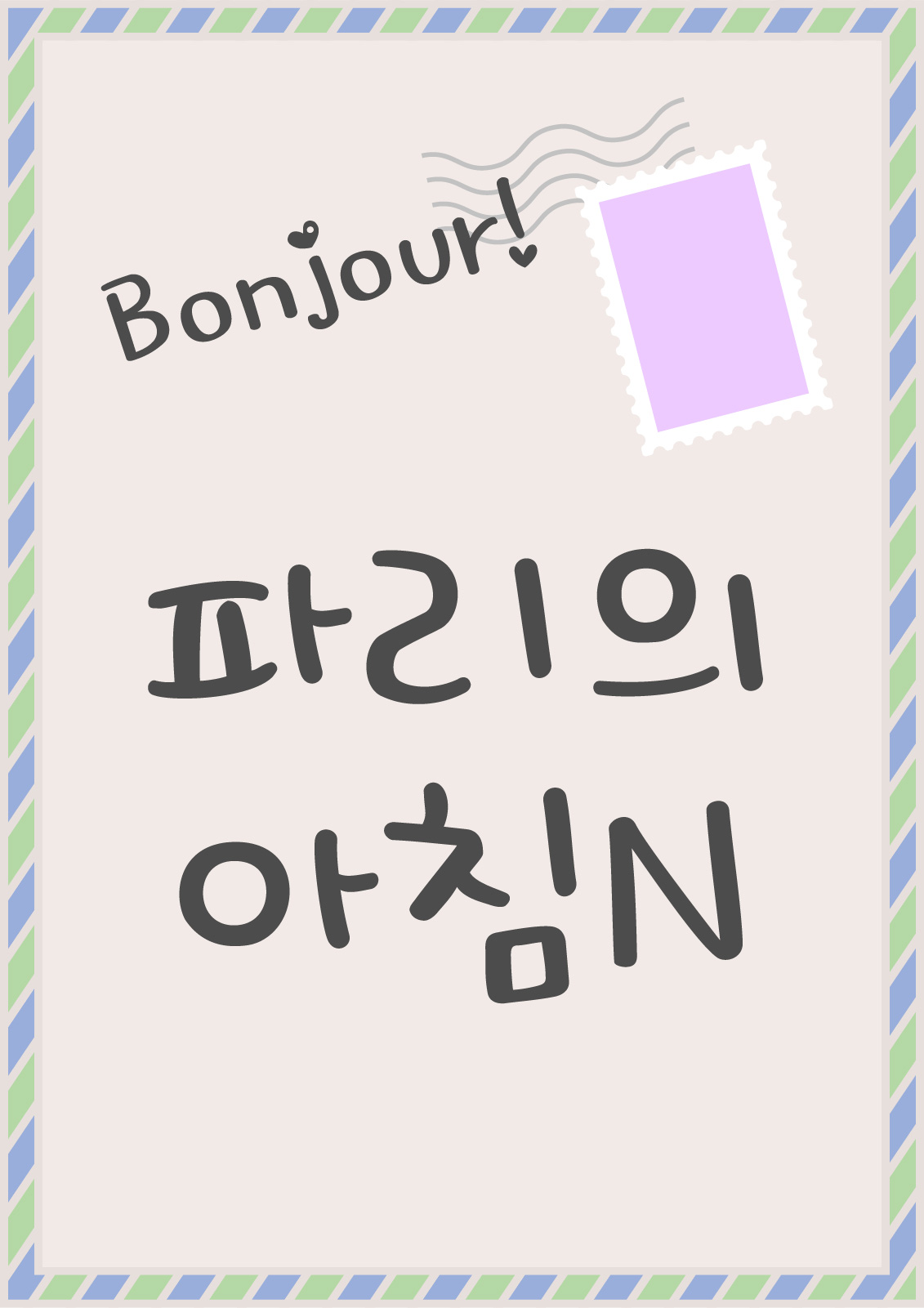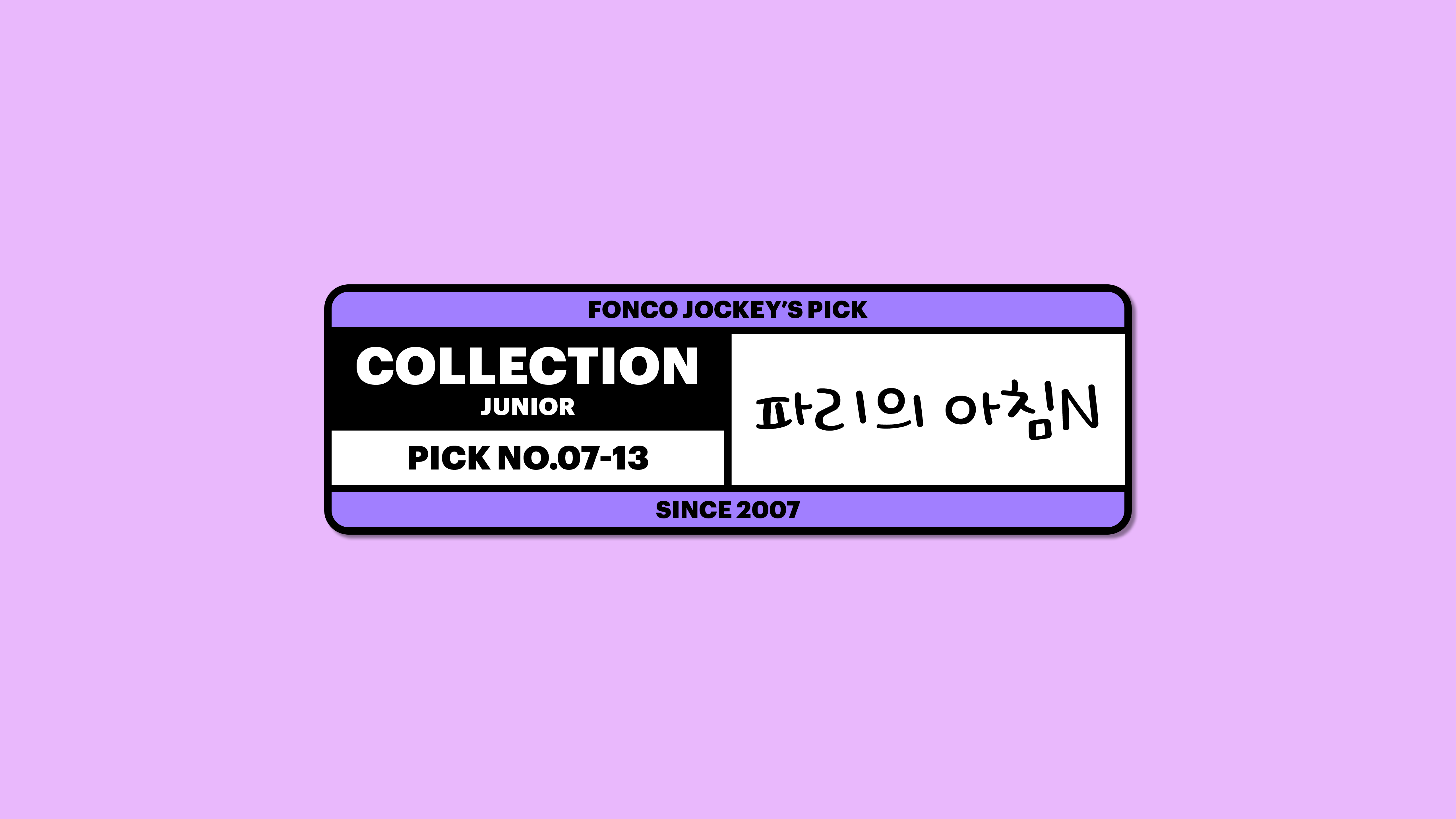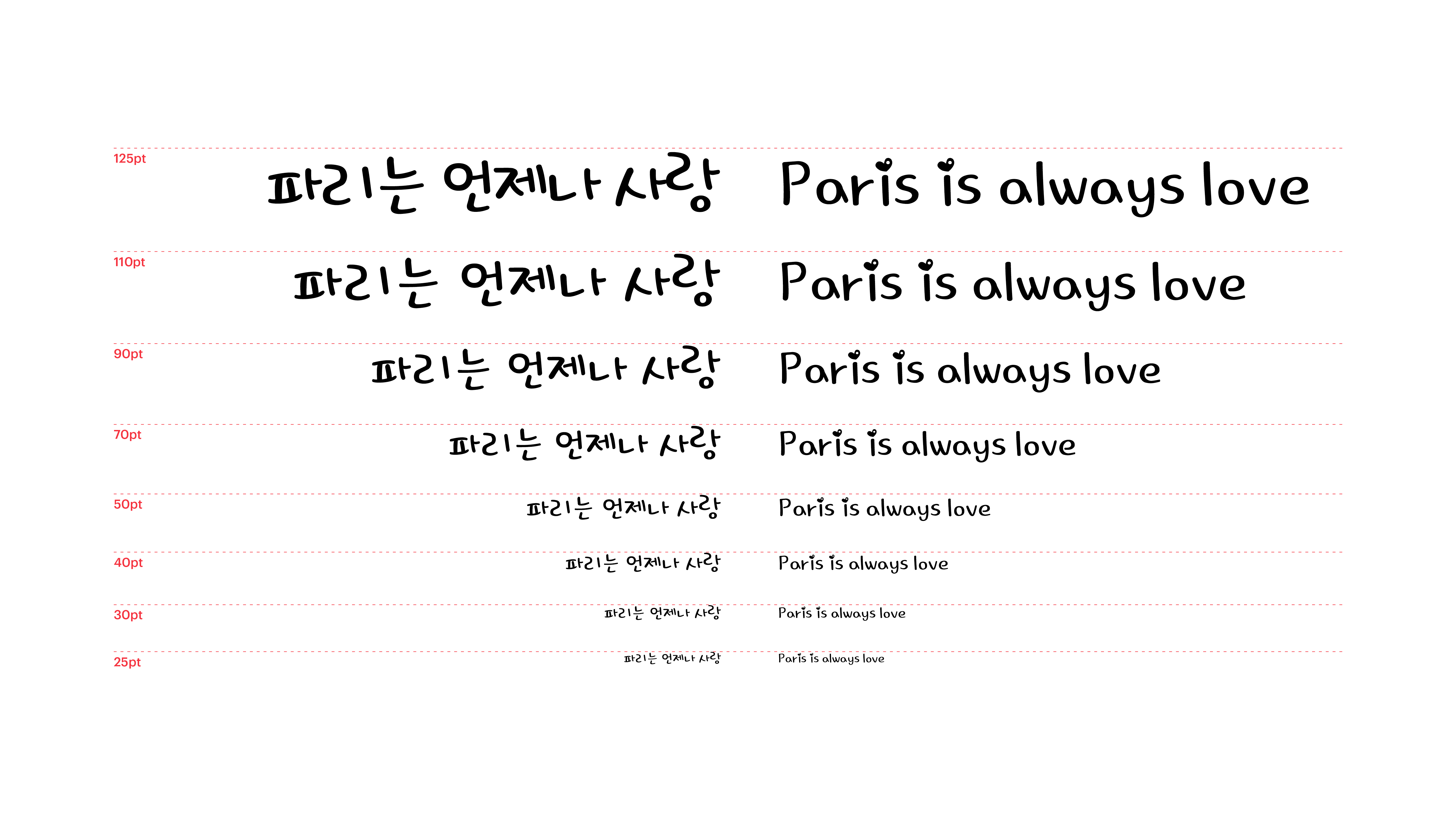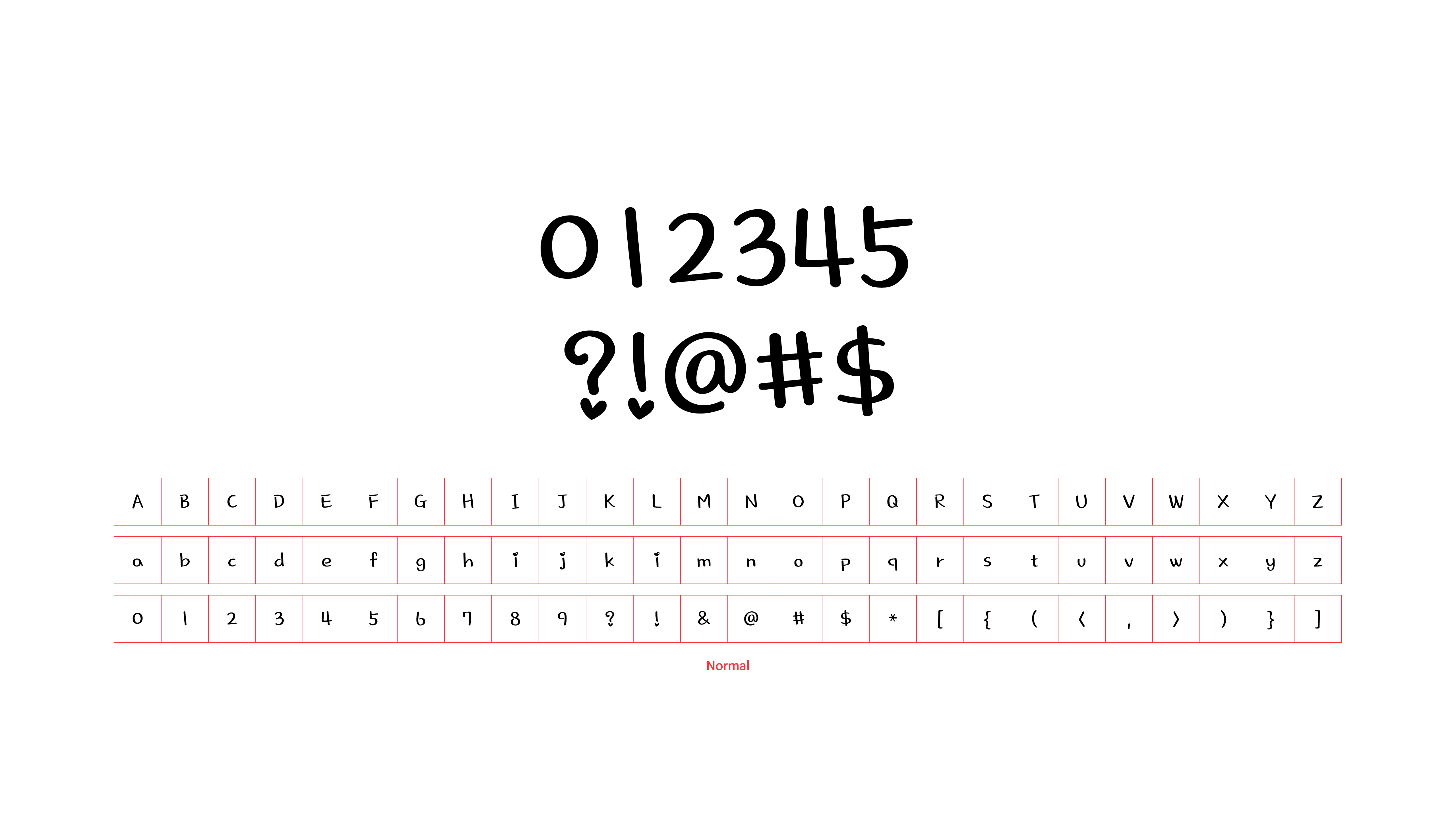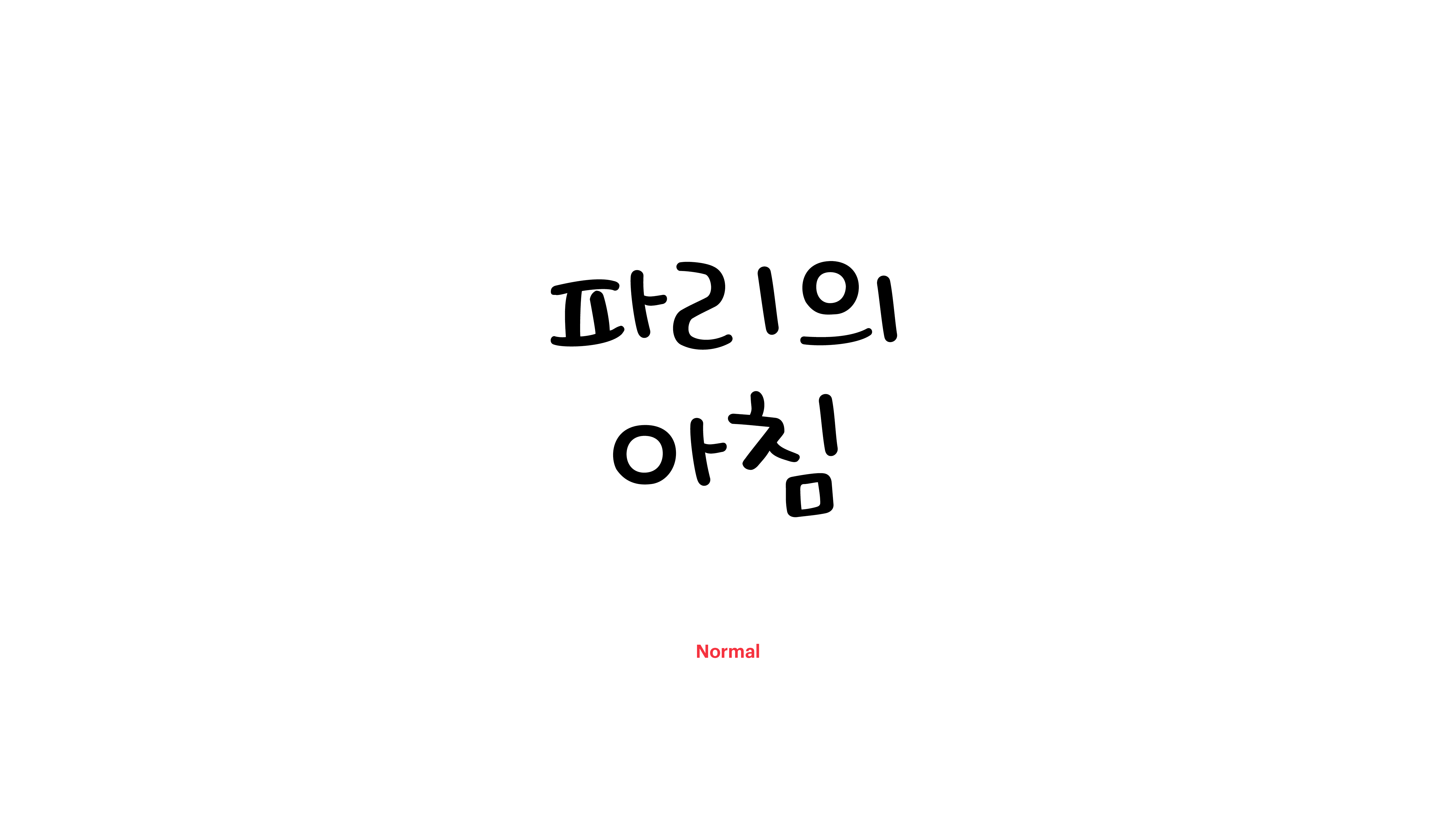
파리의 아침 N
Yoon 파리의 아침N
파리, 하면 무엇이 떠오르나요? 에펠탑, 바게트와 트렌치코트, 마카롱과 거리의 예술가들. 하지만 이 아기자기한 폰트는 파리가 사랑의 도시라고 이야기합니다. 마치 몽마르트르 언덕, 사랑해 벽에 쓰여 있는 세계 각국의 사랑을 읽어가듯 어떤 단어에도 사랑을 담아내는 따뜻한 폰트니까요.